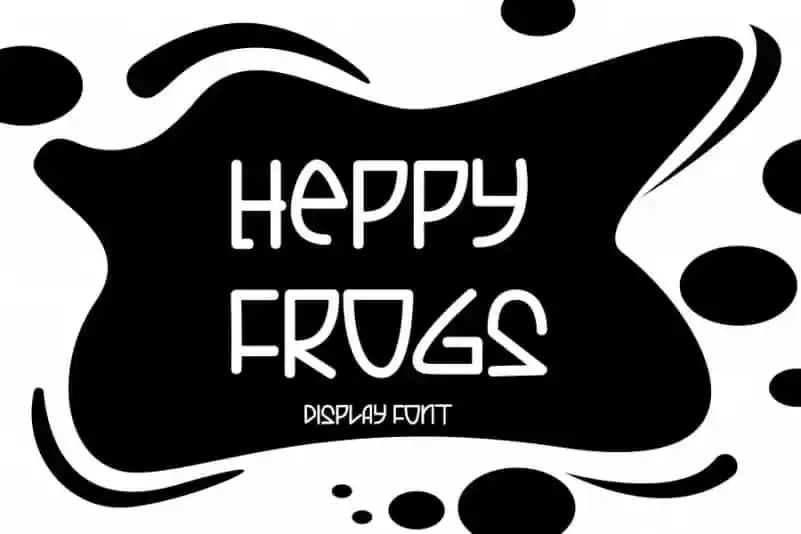
Heppy Frogs Display Font – Download Grátis
A fonte Heppy Frogs Display é uma escolha excepcional para estilos visuais contemporâneos que se destacam com elegância e sofisticação. Com influências chinesas e um toque atual, esta font permite diferentes maneiras de utilização, desde capa de envelope até o título de um documento impresso ou um design de cartão de visita. Suas linhas fluidas e desenhos animados da frita fazem dela uma escolha versátil para projetos que exigem tanto elegância quanto criatividade moderna. Através do uso desta fonte, você pode explorar ideias únicas e interessantes em diferentes formatos de mídia gráfica, garantindo um design atraente e único que se destacará entre as muitas opções disponíveis no mercado.